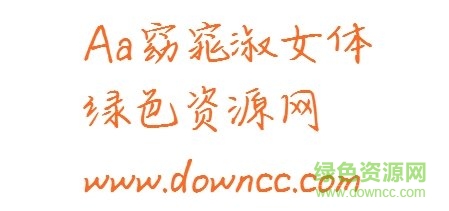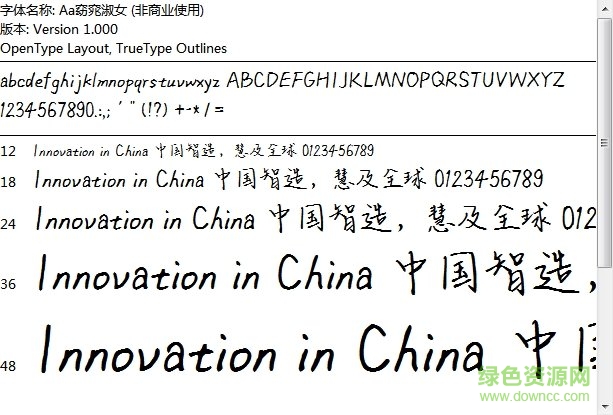
Aa窈窕淑女ttf
窈窕淑女體ttf是一款非常使用的手寫體,字體打破了常見的軟萌可愛之風(fēng),更加端方沉穩(wěn)的造型,讓字跡顯得更加優(yōu)雅不輕浮,是一款閱讀效果極佳的藝術(shù)字體,來綠色資源網(wǎng)下載試試吧!
aa窈窕淑女字體特色
Aa窈窕淑女(非商業(yè)使用)采用常規(guī)風(fēng)格樣式,共有10551個字符。整體效果十分出色,沒有多余的修飾和華麗的點綴,讓文字更加清新質(zhì)樸,可以使用在海報logo設(shè)計、文字印刷排版等諸多領(lǐng)域。
窈窕淑女體